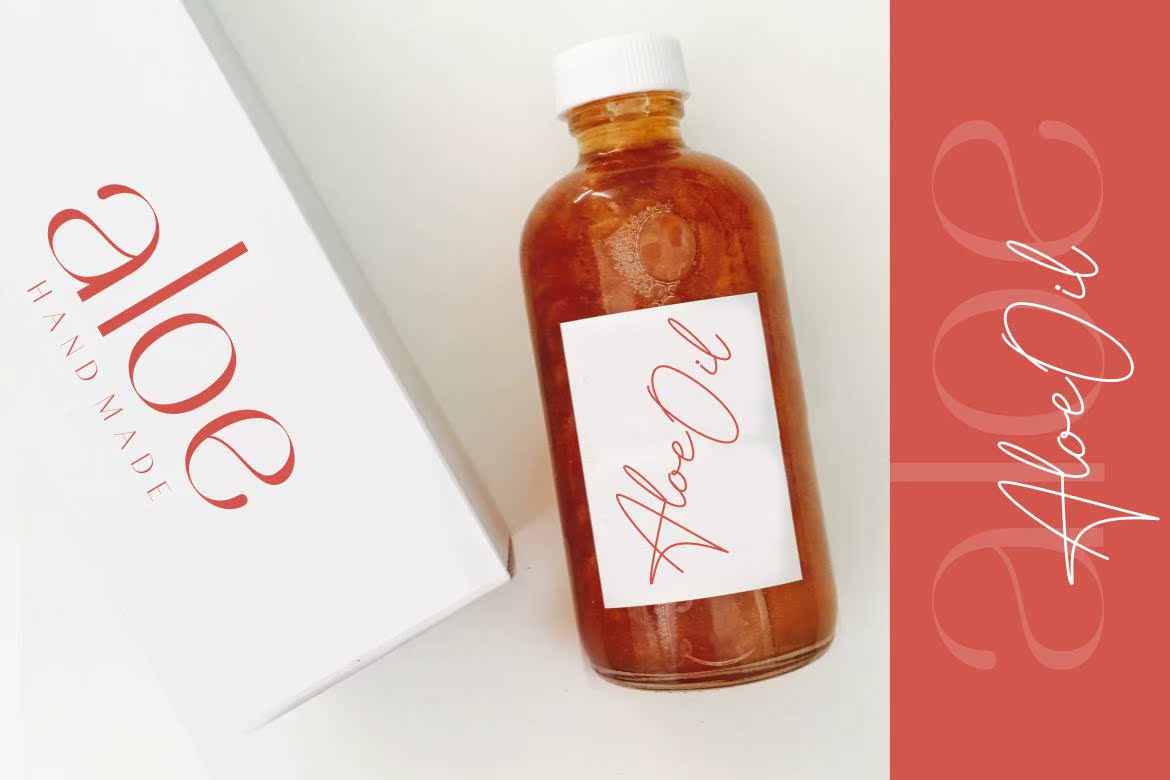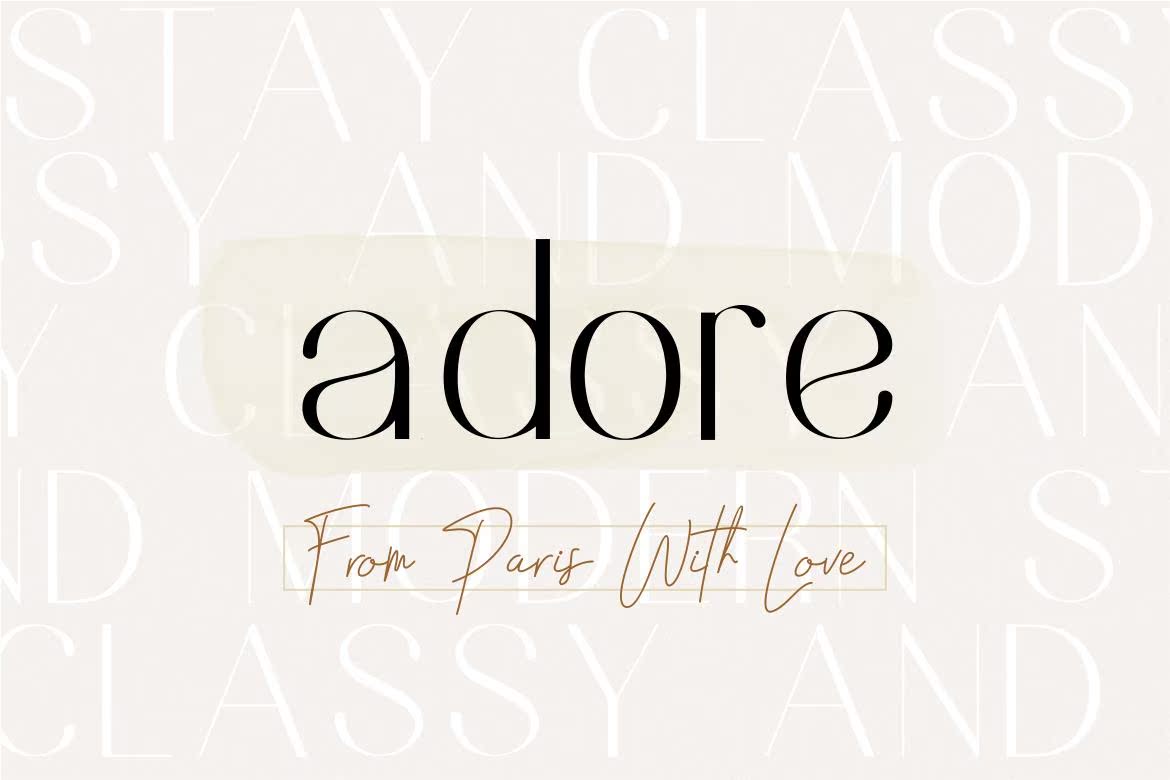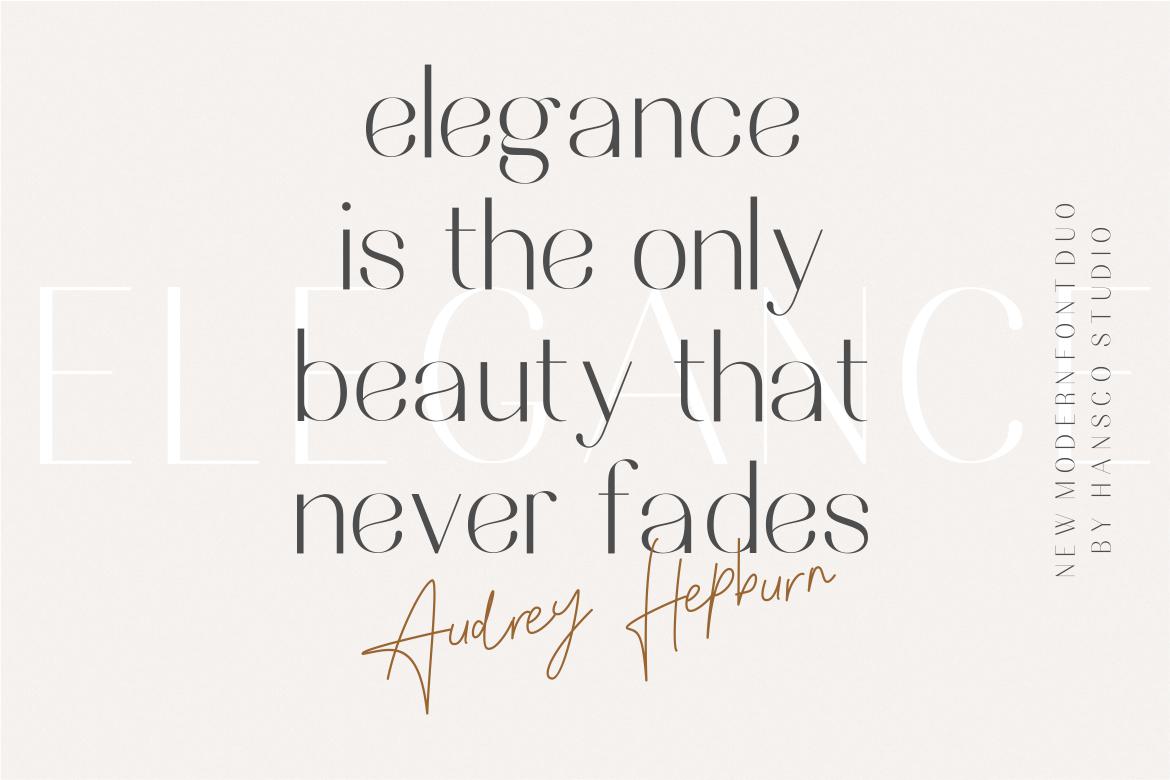
创造一些现代的Leganta和ClassID设计,如Nesansfont和Signature外观时尚优雅的徽标、名片、婚礼庆典、报价、广告、,还有更多。Nesans是一个多方面的东西,没有个性,你会及时回来并获得。用Nesans创造一些美好的今天。创造一些现代的Leganta和Classydesigns。NesansFont和Signature外观圆滑、优雅,用于标识、名片、婚礼宣传、报价、广告、,还有更多。Nesans是一个多方面的人物,你会及时回来并获得。今天,用Nesans创造一些美好的东西。